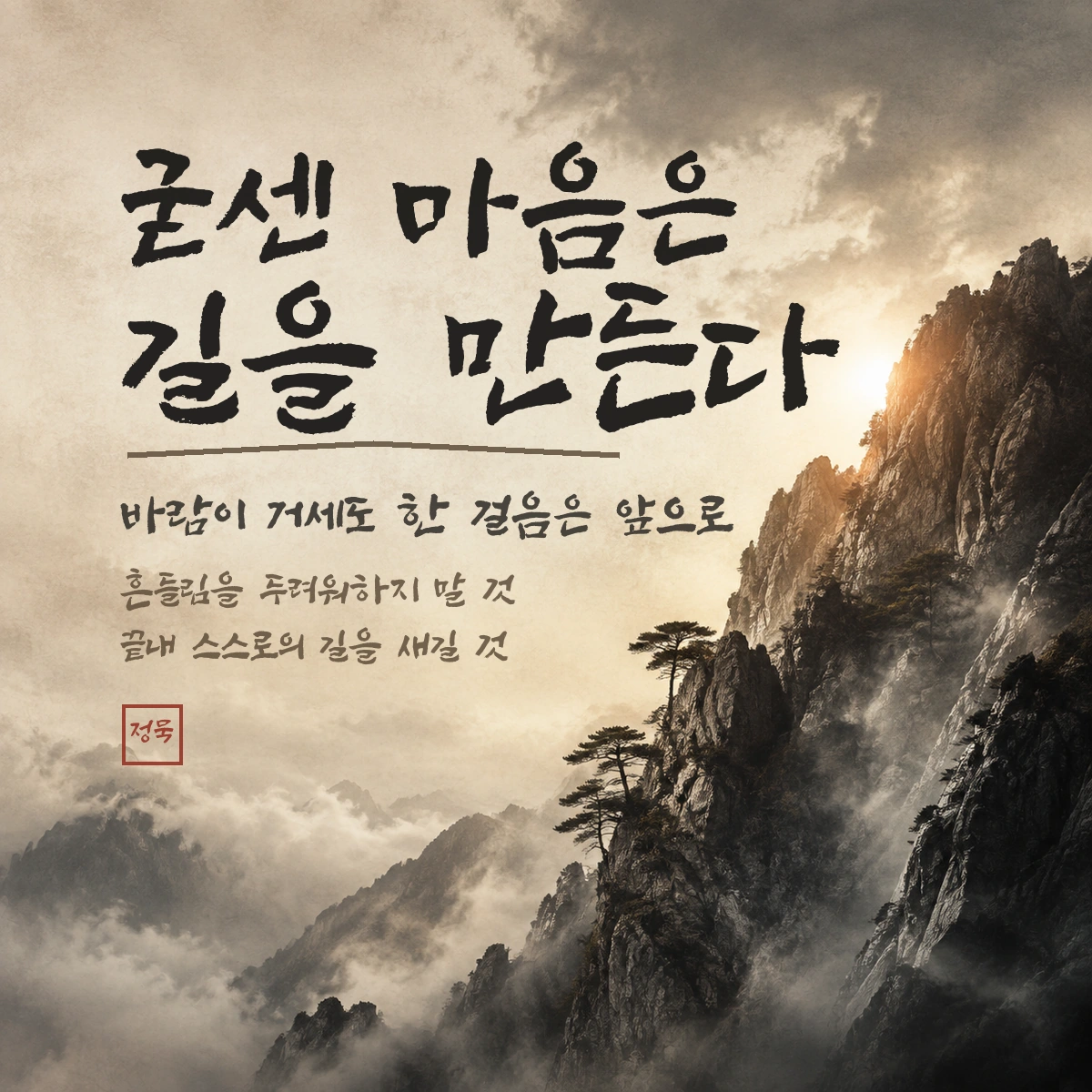
정묵바위체 — 상상토끼에서 배포하는 무료 폰트입니다. 세월의 풍파에도 물러서지 않는 바위처럼, 힘차게 뻗어 나가는 붓의 기운을 담은 캘리그라피 서체
캘리그라피 작가 정묵 김덕수의 글씨를 상상토끼가 2019년에 폰트로 옮긴 서체입니다. 이름의 정묵은 작가의 호입니다. SBS 드라마 복수가 돌아왔다의 타이틀을 비롯해 상업 캘리그라피 작업을 해온 작가이고 대학로에서 캘리그라피 아카데미를 운영하고 있습니다.
이름의 바위가 성격을 그대로 말해 줍니다. 소개문은 세월의 거친 풍파에도 물러서지 않고 버티고 서 있는 바위처럼 우직하고 단단한 서체라고 설명합니다. 영문 이름도 SangSangRock입니다. 붓으로 눌러 쓴 거친 획이 그 인상을 만듭니다.
굵기는 하나이고 한글은 기본 2,350자에 추가 129자를 더해 2,479자입니다. 흔히 쓰는 낱말은 나오지만 드문 음절에서는 글자가 빠질 수 있습니다. 개인과 기업 모두 상업적으로 자유롭게 쓸 수 있고 BI와 CI에도 허용되며 재배포도 가능하지만, 폰트 파일을 수정하거나 유료로 되파는 것은 금지됩니다.